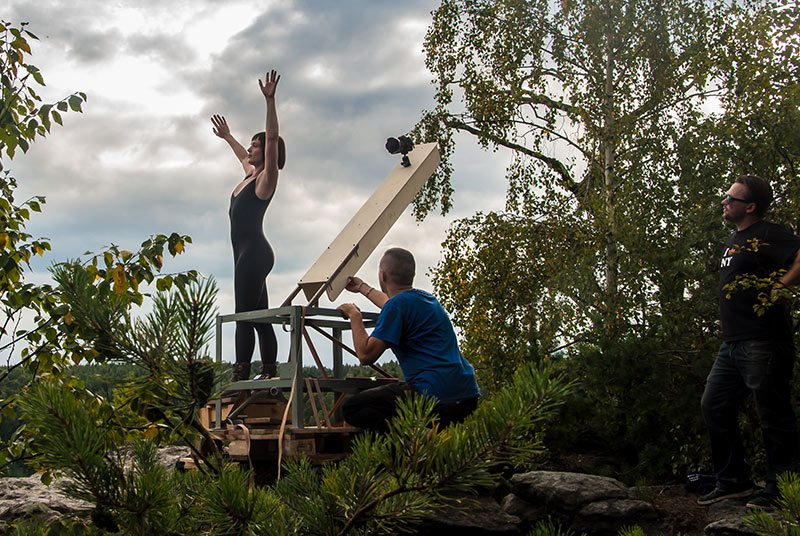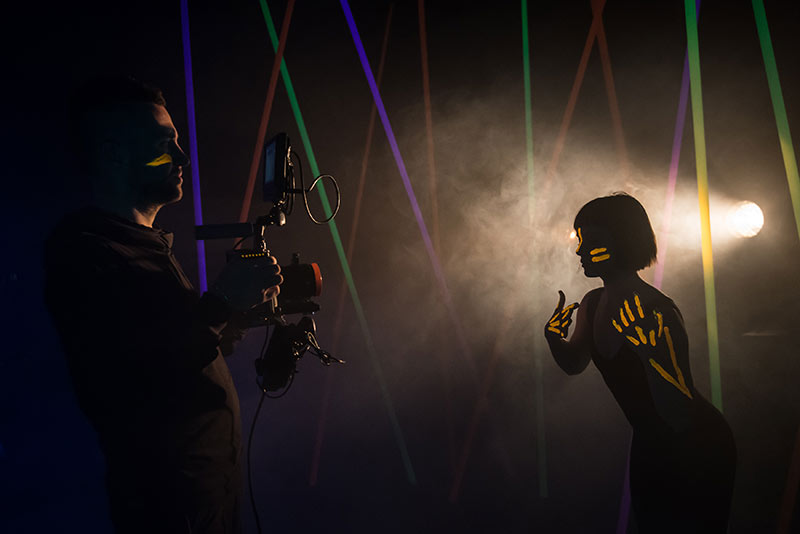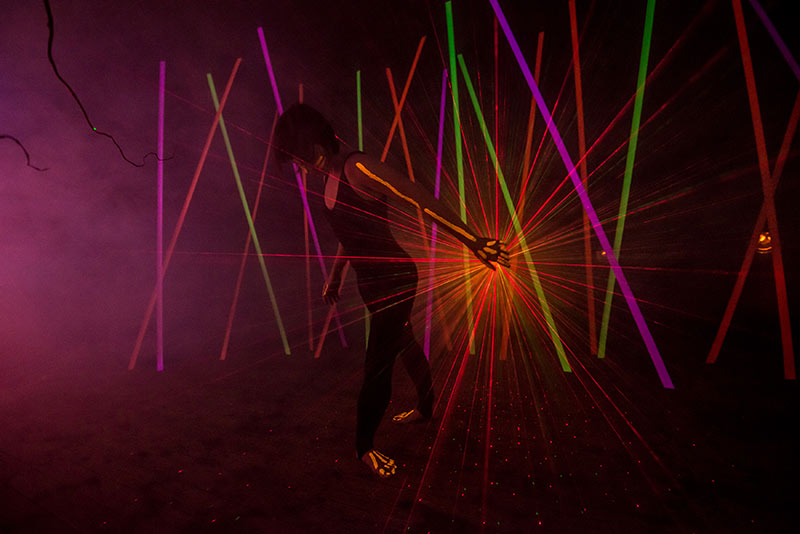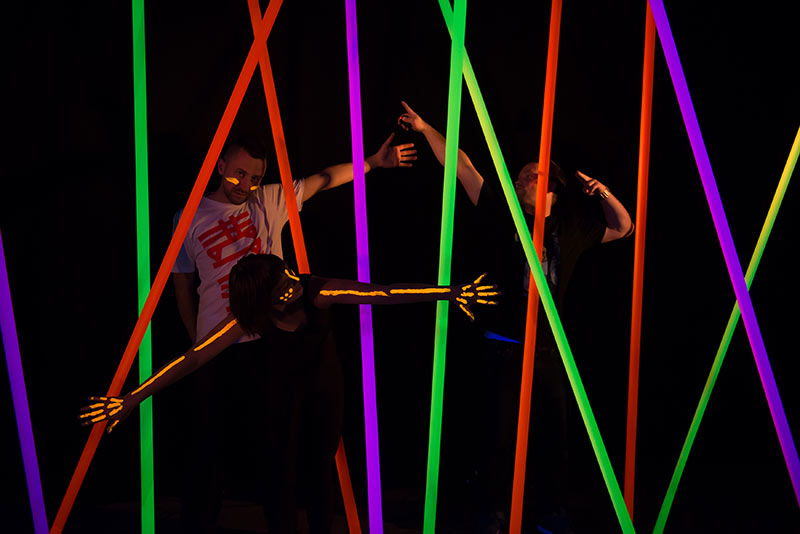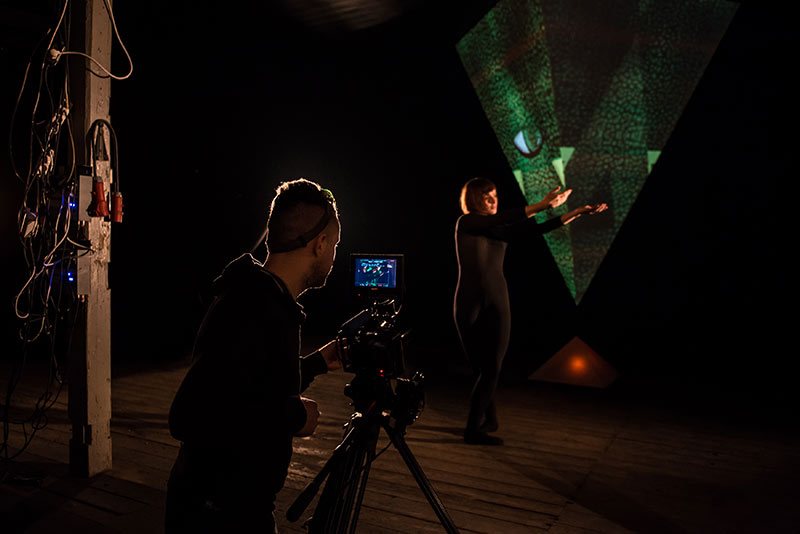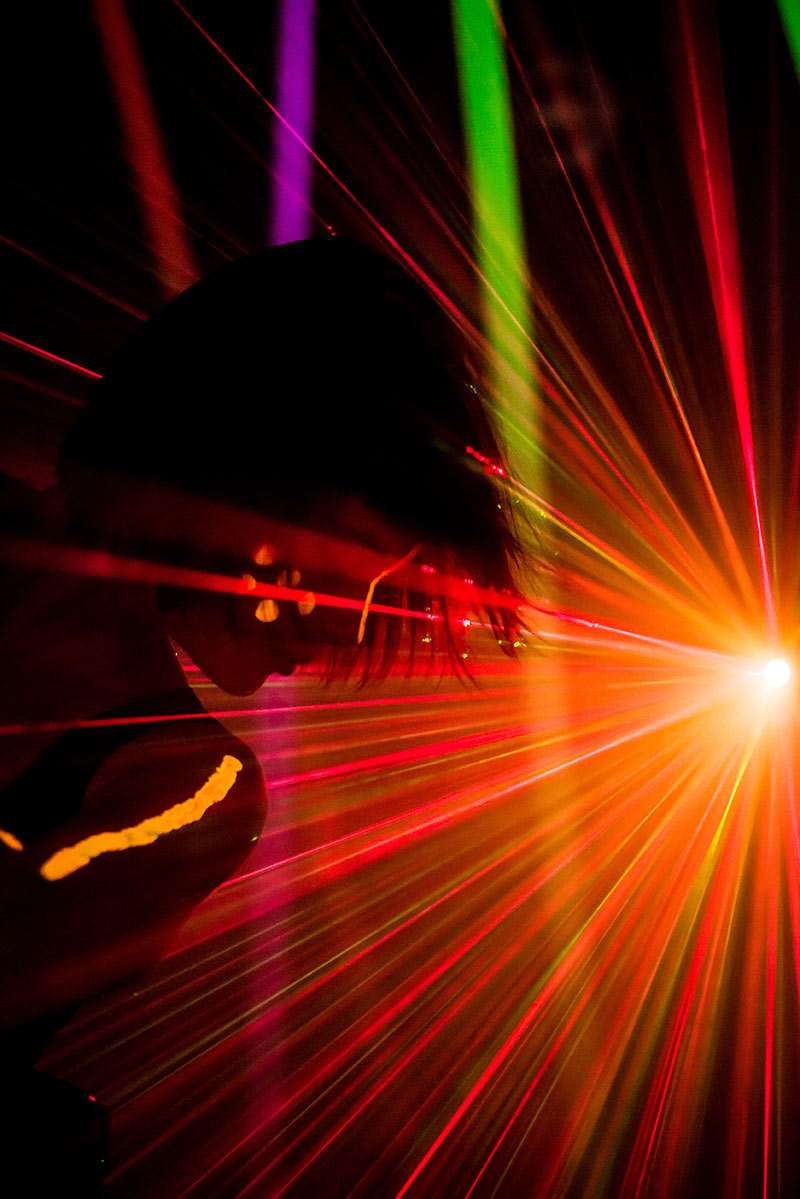
Nach der ersten Vorschau auf der TYPO Berlin ist es nun endlich soweit: Der Tanzfilm des Schriftgestalters und Multimedia-Künstlers Yanone für seine vor zwei Monaten veröffentlichte Schriftfamilie Antithesis ist nun online.
Mit Tänzerin Johanna Roggan, begleitet von Filmmusik von Georg Bauer spielt sich der Film über den Urknall in der Sächsischen Schweiz und in einem improvisiertem Studio ab. Eine hervorragende Arbeit, ein Aufwand der sich gelohnt hat und definitiv sehenswert!
Pressetext: Die Schriftfamilie ist wahrlich Yanones Meisterstück, zieht man in Betracht, dass das Konzept extremer gestalterischer Spannung den Ausgangspunkt für sein Interesse an Schriftgestaltung bildete. Dieses Grundkonzept zog sich von unbedarften Bleistiftskizzen um das Jahr 2000 herum über seine Bewerbungsmappen für die Bauhaus-Universität in Weimar bis hin zu seiner Abschlussarbeit am Schriftgestaltungs-Master Type&Media in Den Haag 2011, wo er die alte Idee wieder aufgriff. Dort legte er erstmals ein stimmiges Konzept für eine Display-Familie vor, das sich der gestalterischen Spannung zwischen drei ungleichen Polen widmete. Gute drei Jahre später erschien die Schriftfamilie nun als FF Antithesis in der FontFont-Bibliothek des in Berlin ansässigen Schriftenverlags FontShop International.
»Drei Pole — es ist die Suche nach Ruhe im dicht gewobenen Netz. Er, der er geschickt hindurch navigiert, wird den Ort der Klarheit finden.«
Was erst als entrücktes Zitat erscheint, das Yanone einst im Weimarer Lokalradio hörte, hat Auswirkungen sowohl auf die Gestaltung der Schriftfamilie als auch auf ihre Anwendung durch den Grafikdesigner. Die drei scharfkantigen Schnitte Normal, Kursiv und Fett unterscheiden sich in ihrer Konstruktion grundlegend voneinander – sprechen aber doch eine gemeinsame Sprache. Ihre Kombinatorik ist es, die den Anwender zur Ruhefindung im dreipoligen Raum zwingt.
Ganz zu schweigen von weiteren Modellen der heiligen Dreifaltigkeit, wie dem philosophischen Modell von These, Antithese und Synthese. Erst die Synthese setzt die vorangegangene These und ihre Gegenthese ins Verhältnis und verhilft beiden dadurch zu ihrer Daseinsberechtigung. So hofft Yanone inständig, dass seine minimalistische »Antithesis« zusammen mit Lucas de Groots »Thesis« (1994), einer der umfangreichsten Schriftfamilien aller Zeiten, dereinst durch eine noch zu entwerfende »Synthesis« durch einen dritten Gestalter ihre Daseinsberechtigung erfahren wird.
Für Yanone alles Grund genug, zur Veröffentlichung der Antithesis maßlos über die Stränge zu schlagen: Er drehte zusammen mit der Dresdner zeitgenössischen Tänzerin Johanna Roggan einen zehnminütigen Tanzfilm – über den Urknall. Denn auch die Existenz des Universums besteht nach indischer Philosophie aus drei Phasen: Der Entstehung, der Dauer, und ihrer Ausflösung. Gedanklich hat Yanone an dem Film gearbeitet, seit er Den Haag 2011 den Rücken kehrte. Ende 2012 folgte ein Trailer und eine nur mäßig erfolgreiche Crowd-Funding-Kampagne. Dass er mittlerweile ein Vielfaches des damals eingespielten Geldes für den Film ausgegeben hat, stört ihn nicht. »Der Film ist unglaublich geworden,« sprüht Yanone vor Begeisterung, »die Bilder, der Tanz, die Musik. Schon die ersten Hörproben der Filmmusik machten den Film zu einem Kunstwerk, noch bevor wir die ersten Bilder im Kasten hatten. Der Musik mit den Bildern überhaupt gerecht zu werden, war eine große Herausforderung.« Georg Bauer ist der Komponist und Produzent der Filmmusik, der unter dem Namen Nocti Luca Psy-Trance-Musik produziert und auflegt. Als er Yanone im Sommer 2011 auf einem Trance-Festival erzählte, er habe schon immer ein Musikstück über den Urknall komponieren wollen, war die Zusammenarbeit besiegelt. Im Frühjahr 2014 konnten sie außerdem noch die Sopranistin Anna Sophia Backhaus dafür gewinnen, der ansonsten digital produzierten Filmmusik eine menschliche Note hinzuzufügen.
Zu den Dreharbeiten in der Sächsischen Schweiz und in Kromsdorf bei Weimar begleiteten Yanone auch der befreundete Fotograf und langjährige Wegbegleiter Daniel Scholz, der die fotografische Bildgestaltung und teilweise auch die Kameraführung übernahm. Daniel war es auch, der bei den Studiodreharbeiten das unglaubliche Foto von Johanna schoss, das dem Film nun als Titelmotiv dient, und das Yanone auch als A1-Plakat auf seinem Online Shop anbietet.